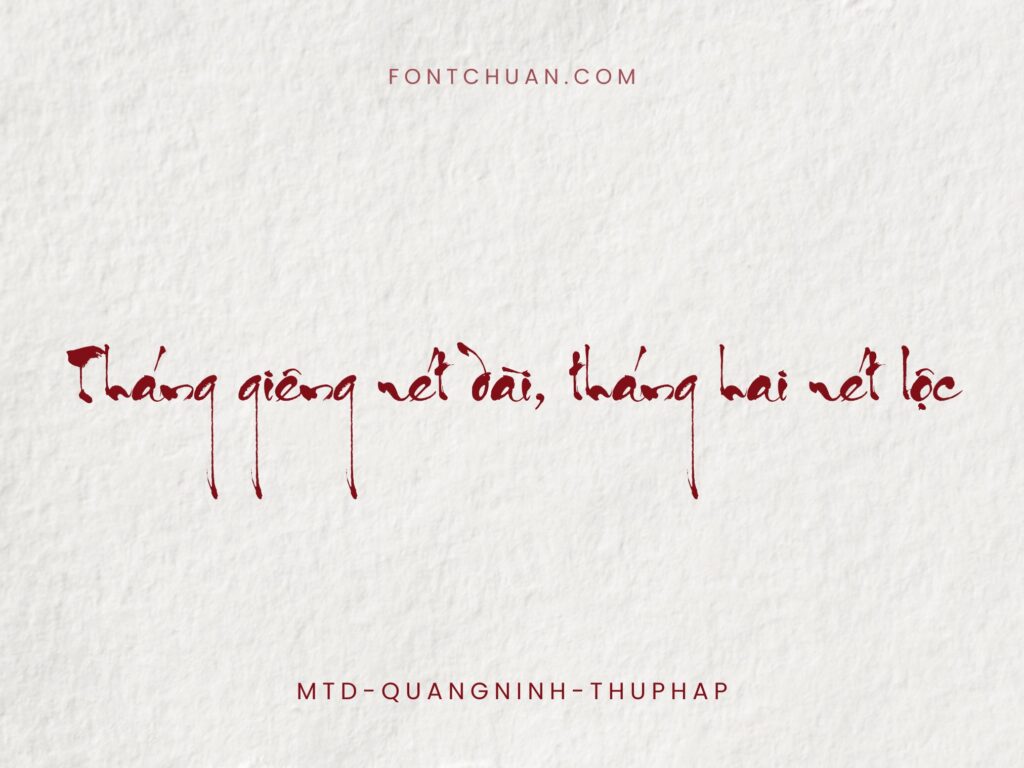
Font Thư Pháp Quang Ninh Trọn Bộ Font Tiếng Việt
Tác giả Font: Quang Ninh
Việt hóa bởi: Quang Ninh
Font MTD QuangNinh Thuphap là một kiểu Font chữ thư pháp độc đáo, được thiết kế bởi tác giả Quang Ninh và Việt hóa bởi Mộc Hạ. Font này hỗ trợ đầy đủ tiếng Việt cùng hơn 90 ngôn ngữ khác, mở rộng khả năng ứng dụng trong các thiết kế đa ngôn ngữ. Đây là một trong những phông chữ thư pháp được cộng đồng thiết kế đánh giá cao và sử dụng trong nhiều dự án sáng tạo, đáp ứng nhu cầu đa dạng của người dùng.
MTD QuangNinh Thuphap nổi bật với các đường nét mềm mại và uyển chuyển, mang đến cảm giác truyền thống và nghệ thuật. Font rất phù hợp cho các thiết kế liên quan đến văn hóa, truyền thống, thiệp mời, bao bì sản phẩm và các ấn phẩm đòi hỏi sự tinh tế và nghệ thuật. Các ngành nghề phù hợp bao gồm quảng cáo, giáo dục, thiệp cưới và ảnh cưới. Font này cũng lý tưởng cho các sự kiện như Tết, Giáng sinh, Valentine và các lễ hội khác.